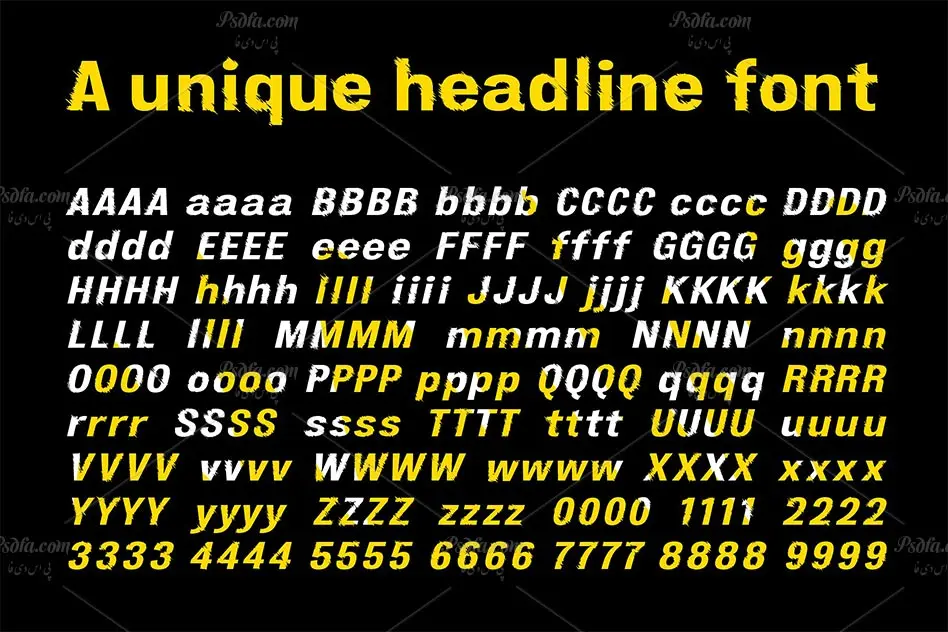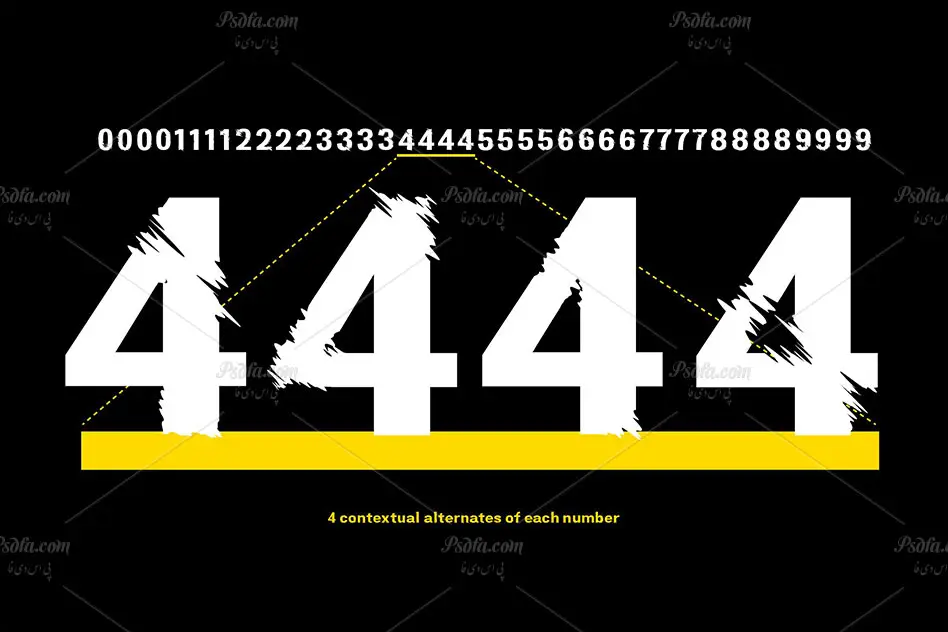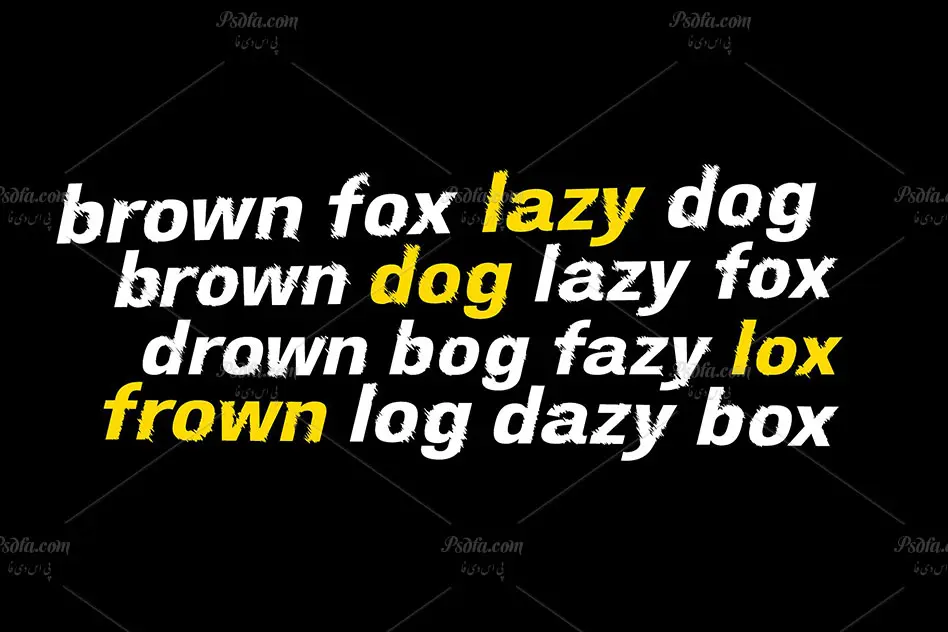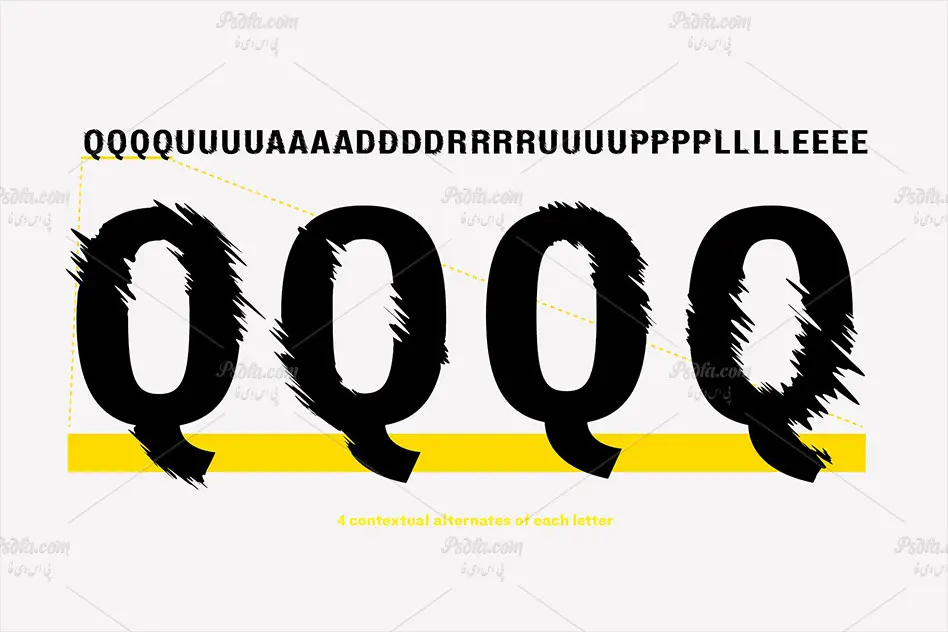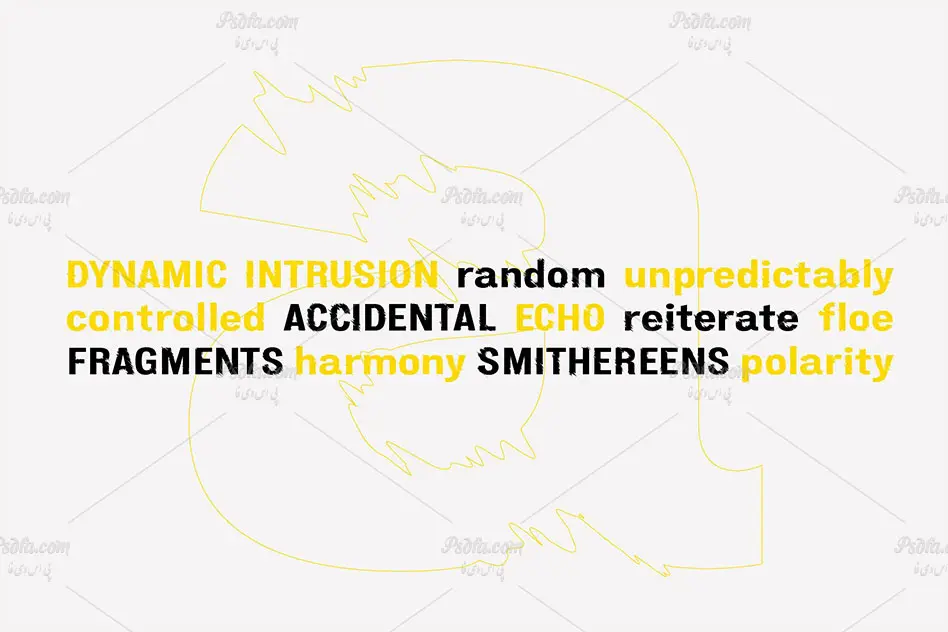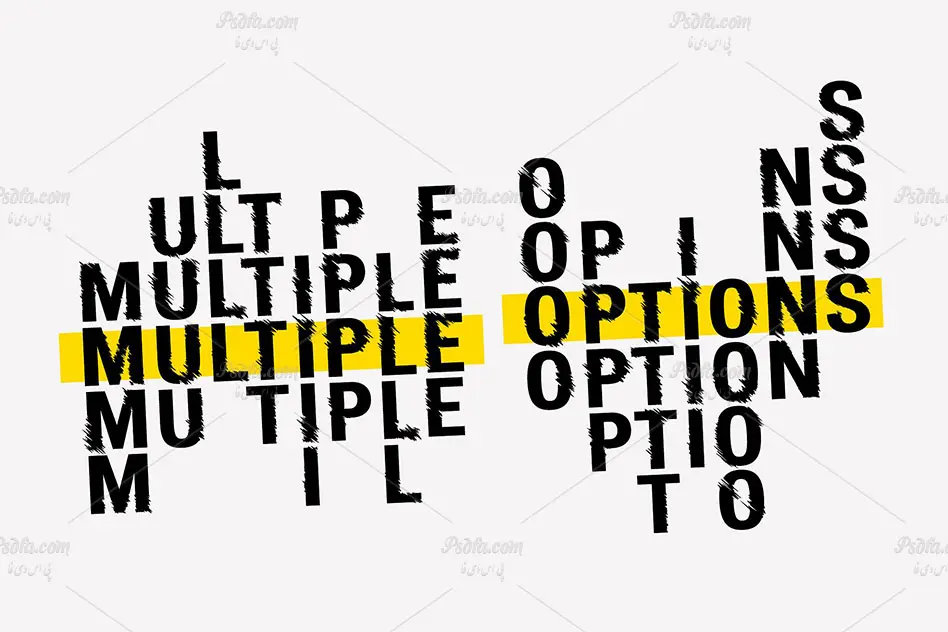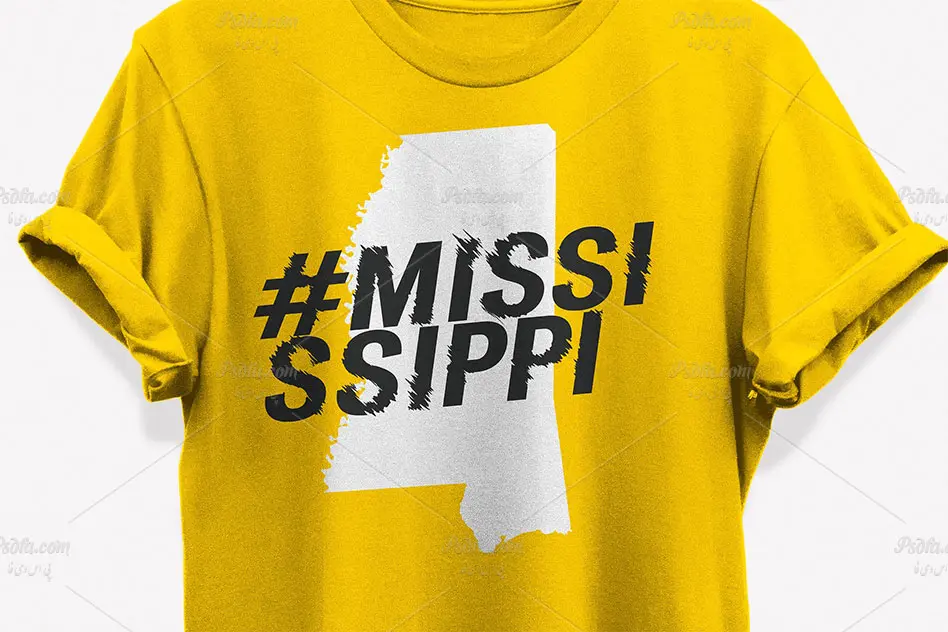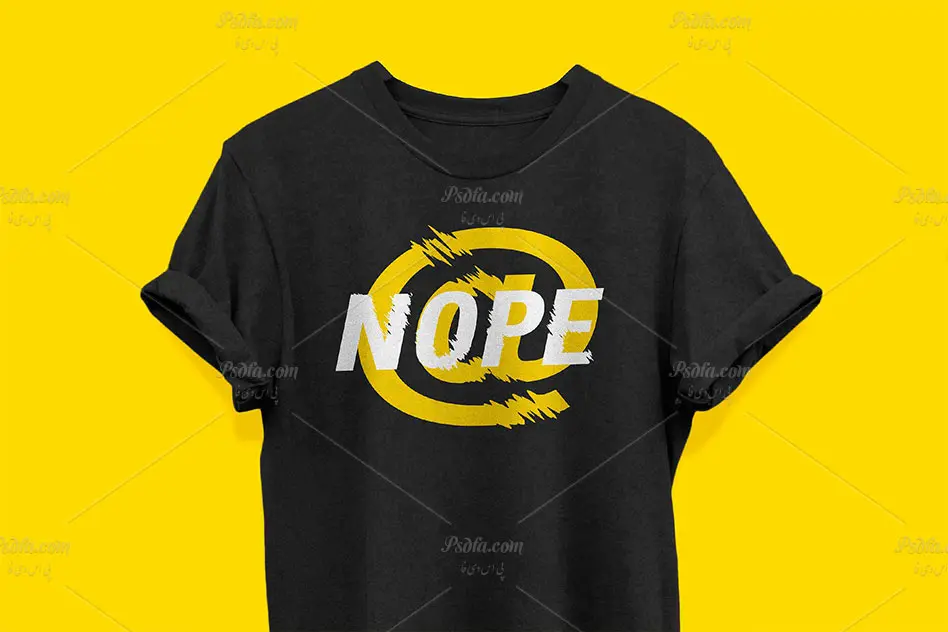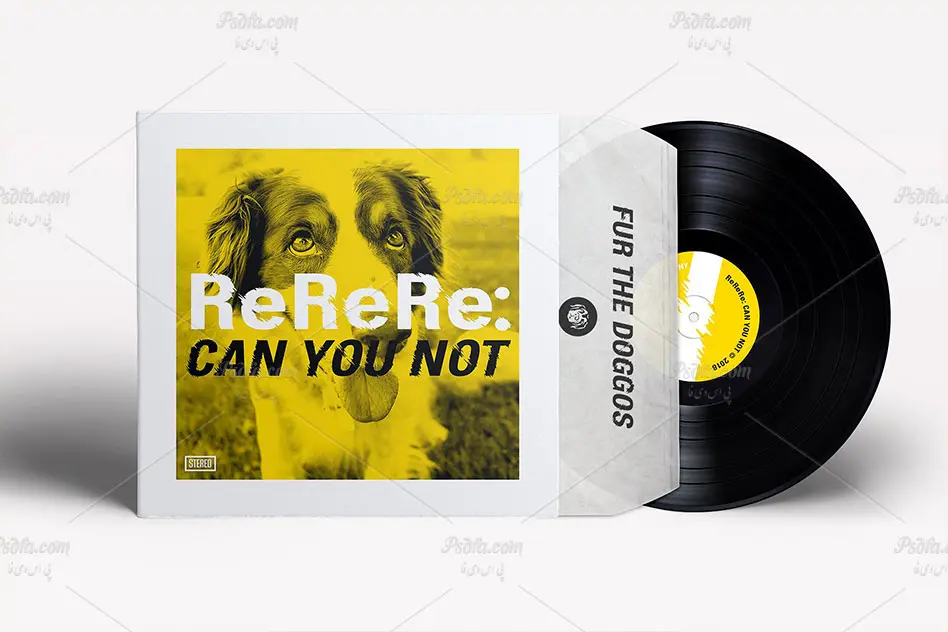
فونت انگلیسی شیار دار Furrow Regular & Oblique
در این مطلب شاهد فونت انگلیسی شیار دار Furrow Regular & Oblique مناسب جهت استفاده در طراحی و گرافیک می باشید. این فونت فوق العاده زیبا در قالب فایل های otf , eot , woff و woff2 در سایت بارگذاری شده اند که با نصب فایل های otf در پوشه فونت های سیستم ، قادر به استفاده از آن ها در تمام نرم افزارهای گرفیکی همچون نرم افزار فتوشاپ ، مجموعه نرم افزار آفیس و … می باشید. از دیگر فرمت های این فونت می توان در طراحی وب سایت نیز استفاده نمود. فونت Furrow در دو سبک Regular و Oblique طراحی شده است که بر حسب نیاز می توانید از هر کدام استفاده کنید. از این فونت می توان در طراحی انواع پوستر ، طراحی وب سایت ، طراحی بر روی پارچه و لباس ، طراحی بر روی بسته بندی محصولات و دیگر موارد استفاده نمود.
- طراحی در دو سبک Regular و Oblique